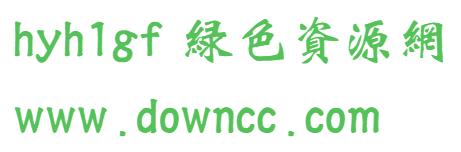
hyh1gf字体(汉仪魏碑繁)是一款朴厚稳重的繁体字体,魏碑字体也属于楷书字体中一种,精美严谨有气势,挺拔朴实,适用于古籍排版、艺术设计等方面,欢迎下载!
魏碑书法笔划严谨、朴厚灵动,丰腴不失于板刻,上承汉隶,下开唐楷,兼有隶楷两体之神韵。它的书法艺术是在汉隶和晋楷的基础上发展演化而来的,堪称汉碑中的上品。